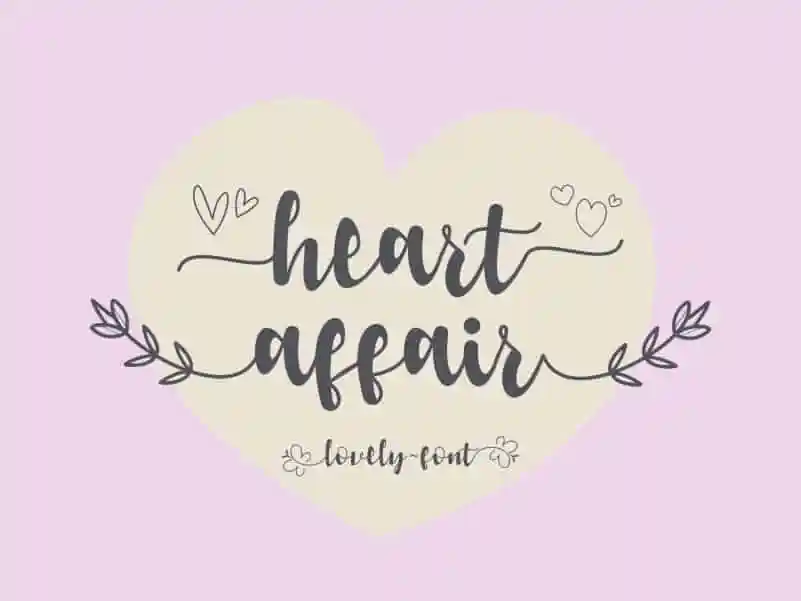
A Heart Affair Font é uma elegante tipografia em estilo script que transmite romance e romantismo. Suas traços suaves e delicados são acompanhados por um ornamento de coração encantador, criando um visual atraente ideal para diversos projetos de design gráfico. Esta fonte original foi concebida para inspirar uma variedade de ideias criativas, desde cartões de lettering até folhas de estação e assinaturas. Ela é perfeita para aqueles que buscam um toque delicado no seu design, seja em cartazes, cabeçalhos ou cartas, esta fonte trará um ar suave e encantador ao seu projeto. Heart Affair Font não apenas complementará sua paleta de cores, mas também dará um toque romântico que certamente se destacará entre a concorrência.